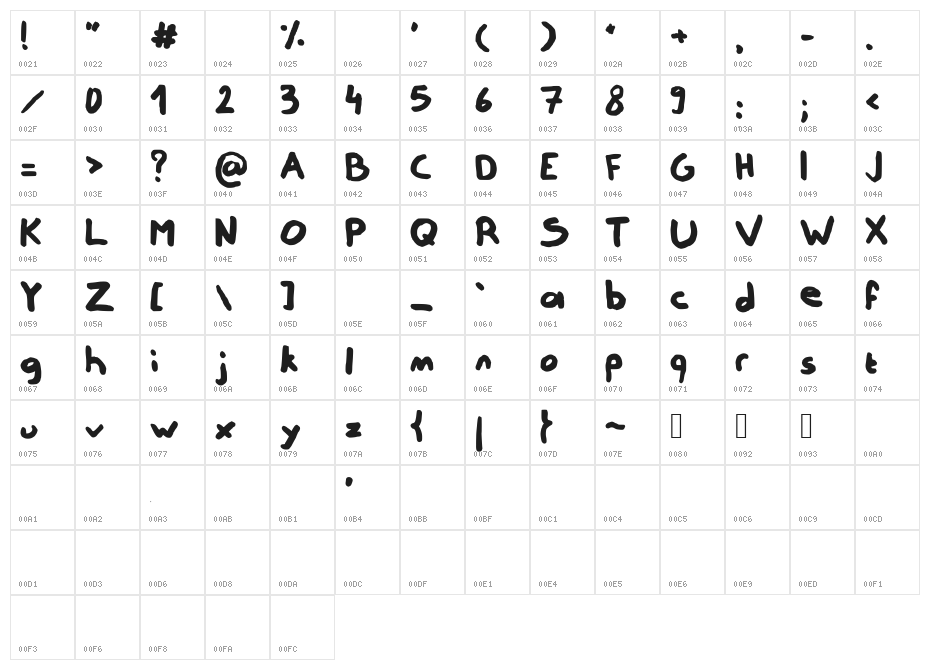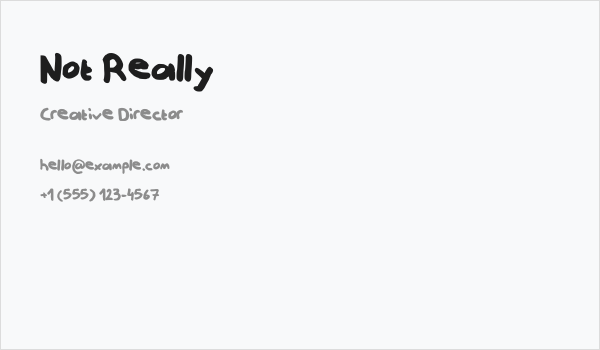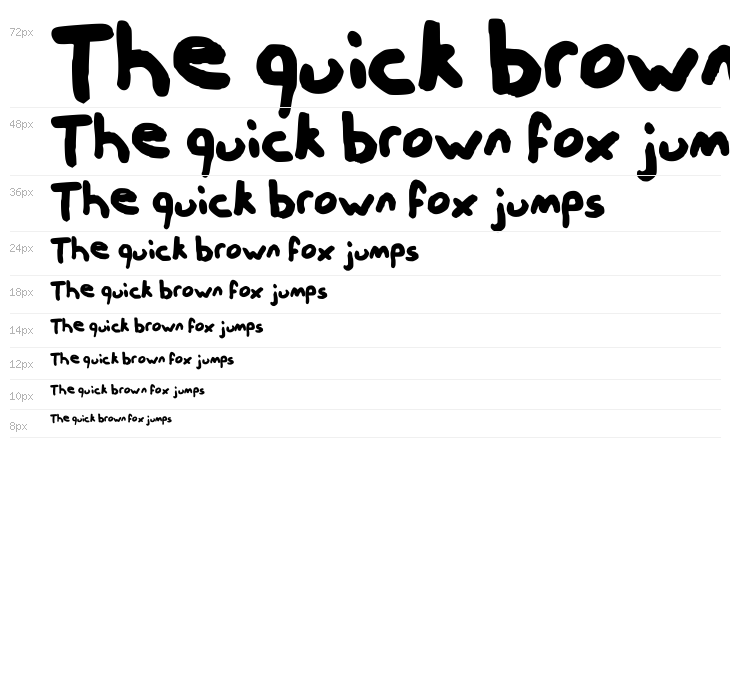
Not Really Font
| Общий стиль | Playful |
| Область применения | Headlines, Logos, Informal Text |
| Рекомендуемые проекты | Ideal for children's books, greeting cards, playful branding, and informal invitations. |